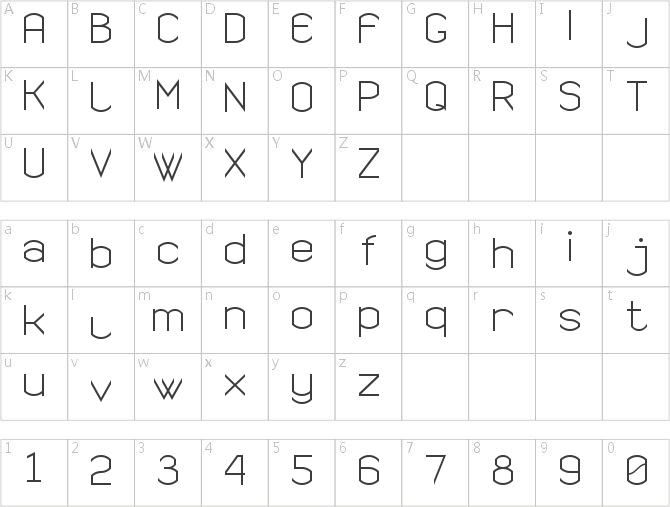
Semi Rounded Sans Serif 7
Semi Rounded Sans Serif 7介绍
Semi Rounded Sans Serif 7字体字库是一款让人赏心悦目、百看不厌的英文字体,适合各类广告和产品包装设计应用,字体大小0.03MB,格式为ttf字体,上传用户是/zyj【GF】,作者/版权方为未知